나의 활자 디자인 철학, 마르틴 마요르 Martin Majoor_전편
골치 아픈 세리프-산세리프체 섞어 쓰기
서적 타이포그래퍼가 아니라면 훌륭한 활자 디자이너가 될 수 없다고 나는 확신한다. 디스플레이용 활자가 아닌 본문용 활자의 경우에 그렇다는 것이다. 활자 디자이너라면 텍스트 내에서 활자가 어떻게 기능하는지 잘 알아야만 하기 때문이다. 서로 다른 종류의 종이마다 활자가 어떻게 반응하는지, 서로 다른 인쇄기법에 따라 활자체가 어떻게 작용하는지, 잘 알아야 한다.
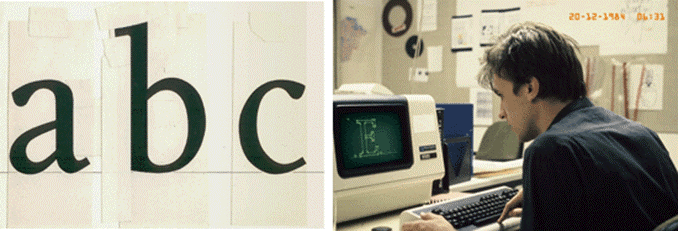
서적 디자이너로서 나는 텍스트 내 여러 요소들을 분명하게 보여주기 위해 하나 이상의 활자체를 필요로 하는 몇몇 복잡한 책을 다룬 바 있다. 산세리프체와 세리프체를 섞어서 쓰는 것은 때로 퍽 유용하다. 다만, 각각 어떤 활자체를 고르느냐가 항상 문제가 되는데, 일반적으로 타임스 뉴 로만(Times New Roman)과 헬베티카(Helvetica)가 섞여서 쓰이곤 한다. 그 이유는 단지 어느 컴퓨터에나 이 폰트들이 깔려있기 때문이다. 이 조합이 최악이라고까지 말하려는 것은 아니다. 뉴스 고딕(News Gothic), 길 산스(Gill Sans), 푸투라(Futura) 같은 산세리프체를 본문용으로 사용하는 것까지는 분명 납득할만하다. 그런데 이 산세리프체들을 어떤 세리프체들과 함께 사용해야 조화를 이룰 수 있을까? 산세리프-세리프 섞어 쓰기가 역사적 지식이나 양식적 지각없이 텍스트에 적용되는 비운의 결말로 치닫는 경우는 허다하다. 미학적 견지에서, 가라몬드(Garamond)/유니버스(Univers)1) , 혹은 보도니(Bodoni)/길 산스의 조합을 대하면 머리가 지끈 아프다. 광고에서는 이런 조합들을 써도 괜찮을 듯 싶다. 광고를 보고 머리가 아파지는 건 오히려 유용한 효과를 가져올 수도 있으니까. 복잡한 텍스트를 다루는 최선의 해결책이란 하나의 공통된 바탕을 공유하는 세리프체와 산세리프체를 섞어 쓰는 법이라는 점이 내게는 점점 분명해졌다. 하지만 어떤 세리프-산세리프체 조합이 이 조건을 만족시킬 수 있을까?
산세리프체의 기원
본문에서 세리프와 산세리프를 섞어 쓰는데 관해 설명하기에 앞서, 산세리프 활자체가 사용되기 시작한 지는 이제 백여 년에 불과하니, 그 기원부터 명백히 짚어 볼 필요가 있다. 최초의 산세리프체는 바로 영국 윌리엄 캐슬론 4세의 활자주조인쇄소로부터 1816년 경 출판된 인쇄물의 활자체라 볼 수 있다. 이 2행 잉글리쉬2) 이집션(Two Lines English Egyptian)이라는 이름의 활자체는 대문자만으로 이루어진 디스플레이용 활자체였다. 이런 다소 어설픈 형태는 어디서 유래했는지는 분명치 않으며, 산세리프 활자체로서의 디자인적 가치는 미미하다.
역주 1) 프랑스어로 ‘위니베르’가 옳은 표기이지만, 익숙한 관습에 따라 ‘유니버스’라는 표기로 통일한다.
역주 2) 디지털 방식으로 활자 크기를 조절할 수 없었던 금속활자 시대에는 크기 별로 각각 다른 폰트를 제작해야 했다. 영국의 활자주조소에서는 대륙의 유럽과 달리 포인트 숫자체계 대신 활자의 크기마다 각각 고유한 이름체계를 붙여서 마치 그 활자의 이름처럼 사용했다. ‘잉글리쉬(English)’는 약 13~14포인트 크기이다. Two Lines는 double과 같은 뜻으로 쓰였으며, 이는 위아래 2행을 차지하는 크기라는 뜻이니 ‘2행 잉글리쉬(Two Lines English)’는 잉글리쉬의 2배인 26~28포인트 크기를 의미한다.
▶ 윌리엄 캐슬론 4세의 활자주조인쇄소에서 1816년 경 출판된 디스플레이용 산세리프 활자체
이보다 1898년 독일 베를린의 베르톨트 활자주조소에서 출시된 악치덴츠 그로테스크(AkzidenzGrotesk)의 경우가 훨씬 흥미롭다. 이 산세리프 활자체는 출시되자마자 굉장한 성공을 거두었고, 여러 활자주조소에서 곧 이를 다투어 모방하기 시작했다. 당시의 여느 산세리프체들과 마찬가지로, 악치덴츠 그로테스크는 디스플레이용 활자체로 사용하려는 의도로 제작되었다. 독일어로 악치덴츠슈리프트(Akzidenxschrift)는 서적의 본문용 활자가 아닌, 잡다한 광고매체의 디스플레이용 활자를 의미하기도 한다. 한편 악치덴츠 그로테스크는 소문자까지 포함하고 있어서 본문용으로도 걸맞았다. 그렇다면 이 악치덴츠 그로테스크는 어디에 형태적 근간을 둘까? 최초의 인쇄용 활자들은 15세기로부터 거슬러왔는데, 이들은 필체를 모방한 세리프 활자체들이었다. 19세기 산세리프체가 등장하던 시기에, 이 산세리프 활자체들이 근간으로 삼을 수 있는 건 당시에 통용되던 세리프 활자체들 뿐이었다. 악치덴츠 그로테스크의 각종 웨이트(weight) 대부분은 자의식 강한 활자 디자이너가 아니라, 베르톨트나 여타 다른 활자주조소의 능숙하지만 이름없는 펀치제작자들이 깎아서 만들었다.
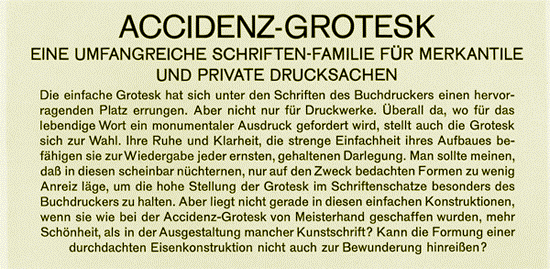
▶ 베르톨트 활자주조소에서 1898년 출시된 악치덴츠 그로테스크
이는 펀치제작자들이 세리프를 결여한 형태를 둘러싼 일반적인 견해를 공유해야 했다는 뜻이니, 그들은 아마 발바움(Walbaum)이나 디도(Didot)처럼 당시에 잘 알려져 있던 모던스타일3) 로만체의 형태로부터만 그렇게 합의된 견해들을 끌어낼 수 있었을 것이다. 발바움과 악치덴츠 그로테스크의 낱자들을 겹쳐놓으면 이 사실이 명확히 드러난다. 이 두 활자체는 바탕 형태, 다시 말해 골격이 일치한다.
역주 3) 원문에는 classic과 classisistic이라는 용어를 사용했다. 르네상스 로만체(세리프체)는 올드스타일, 바로크 로만체는 과도기형, 고전주의 로만체는 모던스타일을 의미한다.
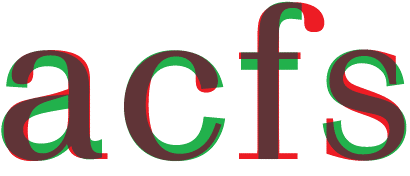
◀ 악치덴츠 그로테스크와 발바움을 서로 포갠 모습
하지만 이들 모던스타일 활자체들은 산세리프체가 근간으로 삼을만한 좋은 모델과는 거리가 멀다. 발바움의 경우, 소문자 c와 숫자 2, 5같은 낱자들에서 가늘게 맺어지는 꼬리는 우아하지만, 이 가느다란 부분들이 산세리프에서는 그저 두꺼워지기만 하면서, 결국은 거의 ‘닫혀진’ 형태로 귀결된다. 악치덴츠 그로테스크는 발바움으로부터 나온 것이라 할 수 있으니, 텍스트에서 이 두 활자체를 섞어 쓰는 것은 봐줄 만한 조합을 이룬다.
◀ 발바움의 가늘게
맺어지는 꼬리
1916년, 최초의 산세리프체가 출시된 지 정확히 100년 되던 해에, 영국의 캘리그래퍼인 에드워드 존스턴(Edward Johnston)은 런던지하철을 위한 활자체를 디자인한다. 이 존스턴 산스(Johnston Sans)의 대문자들은 분명 캐슬론 올드 페이스(Caslon Old Face)가 근간이기는 하나, 소문자들은 에드워드 존스턴의 캘리그라피적 솜씨의 산물이다. 산세리프체가 기존의 세리프 활자체 아닌, 납작 펜으로 쓴 필체에 근간을 둔 건 이 소문자들이 처음이다.
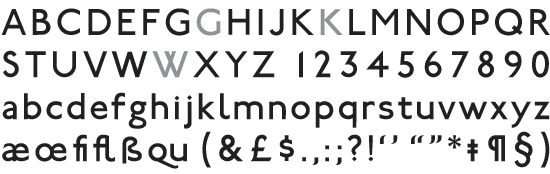
▶ 존스턴 산스, 에드워드 존스턴의 런던지하철 알파벳, 1916년
돌에 글자를 새기는 것으로 활자 디자이너의 길로 들어선 에릭 길(Eric Gill)은 모든 면에서 비범한 활자 디자이너였다. 그는 세리프 활자체가 어떻게 보여야 하는지에 대한 진정한 이해를 가지고 인쇄용 활자를 디자인 했다. 그리고 1928년, 그는 길 산스를 만들었다. 길 산스는 산세리프체였지만, 돌에 세리프체 글자 형태를 새기는 경험이 녹아들어 있었다. 본인 스스로 의식한 것은 아니지만, 길 산스는 그가 머릿속에 구상해둔 특정 세리프체를 근거로 했다. 길 산스와 세리프 달린 그의 파트너 조안나(1930년)를 섞어 쓰는 것은 타이포그래피적으로도 조화로운 지면을 창출해낸다. 조안나는 일종의 길 산스 아베크4) 인 것이다! 에릭 길이 애초부터 조안나와 길 산스를 하나의 패밀리(family)로 계획하기만 했어도, 그는 세리프와 산세리프를 동시에 한 패밀리로 디자인한 역사상 최초의 인물이었을 것이다.
역주 4) ‘세리프 달린 길 산스’라는 의미로, 저자의 언어유희이다. 세리프가 없을 때 프랑스어 sans(without)라는 표현을 쓰므로, 세리프가 달렸다는 뜻의 이름을 프랑스어 avec(with)로 표현했다.
◀ 길 산스(1928년)와 조안나(1930년)
1927년에는 파울 렌너의 푸투라가 출시되었다. 이 산세리프 활자체는 악치덴츠 그로테스크의 근간이었던 한 물 간 모던스타일 글자형태를 모태로 삼는 대신, 스크래치 드로잉으로부터 출발했다. 푸투라는 자형이 대단히 구조적이어서 바우하우스 운동과 구성주의적 이념의 영향을 받은 듯 보이지만, 실은 전혀 그렇지 않다. 오히려 렌너는 로마시대 비문에 새겨진 대문자들처럼 고전적인 원칙에 입각하여 푸투라를 디자인했다. 균형을 잘 갖춘 본문용 활자체이면서도, 당시 유행하던 바우하우스 운동의 아우라를 가지고 있다는 점, 이것이 바로 푸투라의 성공 요인 중 하나였다.
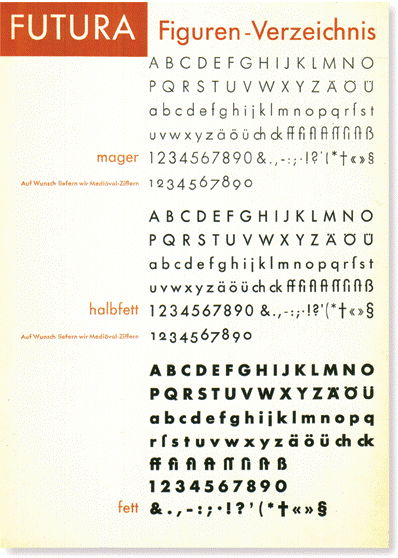
◀ 푸투라(1928년)의
활자 견본집
1957년경에는 푸투라같은 전쟁 전의 기하학적 활자체들에 대한 일종의 반향으로 헬베티카(Helvetica)를 비롯하여 그 아류들이 숱하게 쏟아졌다. 이 활자체들은 빠짐없이 예의 악치덴츠 그로테스크에 바탕을 두었고, 이내 엄청난 인기를 끌었다. 기존 산세리프체를 기본으로 새로운 산세리프체를 만드는 데에는 비용이 보다 적게 들었으니, 이들 활자체들이 악치덴츠 그로테스크와 비교할 때 어떤 새로운 특징도 갖지 않는다는 사실이 이상할 것은 없었다. 악치덴츠 그로테스크보다 나아진 척 위장하지만, 사실 헬베티카는 악치덴츠 그로테스크의 매력인 투박함과 개성마저 잃은 활자체일 뿐이라 생각한다. 1982년 출시된 애리얼은 최악이라 할 만하다. 헬베티카를 거의 일대일로 따라 만들었으니, 애리얼이야말로 표절의 궁극적 표절이라 하겠다.
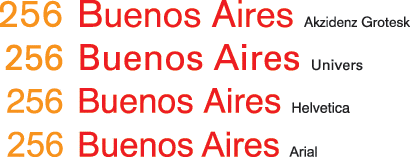
◀ 악치덴츠 그로테스크(1898), 유니버스(1954), 헬베티카(1957), 애리얼(1982) 비교
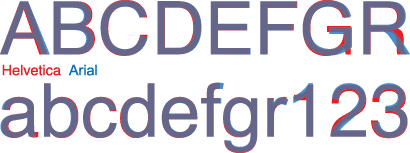
◀ 헬베티카(1957)를 거의 일대일로 따라 만든 애리얼(1982)
악치덴츠 그로테스크의 온갖 모조품 가운데, 유니버스는 활자 디자인으로서는 새로웠던 강력한 특징을 하나 지녔다. 서로 완벽하게 섞어 쓸 수 있는 21개 웨이트와 자폭이 거의 과학적이라 할만한 하나의 체계 속에 구성되었던 것이다. 유니버스는 웨이트와 자폭들이 명확한 체계성을 결여한 채 난무하던 산세리프 활자체들의 정글에 제시된 탁월한 응답이었다.
1997년, 유니버스는 60개가 넘는 버전으로 온전히 새로 그려졌다. 이는 불행히도 개선된 방향이 아니었다. 없어도 무관한 버전들이 이제 너무 많아졌고, 자간은 너무 좁았으며, 12도 각도로 기왕에도 상당하게 기울어져있던 이탤릭체는 15.5도라는 황당한 각도로 쓰러지기에 이르렀다. 예의 성공한 활자체를 새로 디자인하는 것은 활자 디자이너가 고려함직한 일이 못 된다고 생각한다.
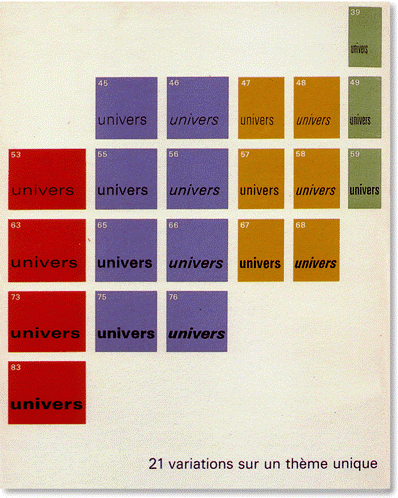
▲ 로물루스의 세리프 버전과 산세리프 버전을 포개어 본 모습
이 글은 2002년, 아르헨티나 부에노스 아이레스의 「티포흐라피카(TipoGrafica)」 53호에서 ‘나의 활자 디자인 철학(My Type design Philosophy)’라는 제목으로 처음 출판되었다. 2006년에는 얀 미덴도르프와 에릭 슈피커만이 편집한 책 ‘메이드 위드 폰트폰트(Made with FontFont)’에서 ‘넥서스 원칙(The Nexus Principle)’이라는 제목으로 업데이트한 글을 새로 실었다.
2009년 마르틴 마요르는 자신의 홈페이지에 이 글을 다시 개정증보한 후 업데이트했다.